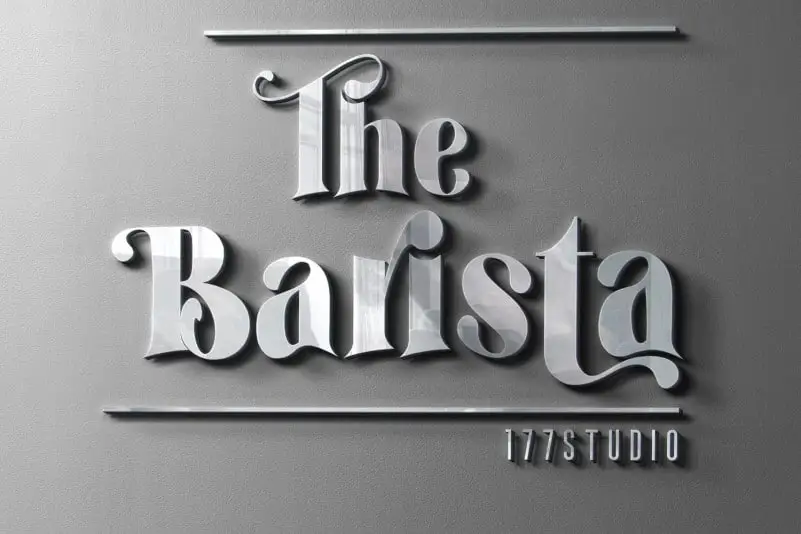
The Barista – Serif Font – Download Grátis
Introduzimos The Barista Serif Font, uma elegante serif que combina detalhes únicos com um toque moderno. Inspirada nas antigas marcas e tipografia vintage, a fonte apresenta belas ligaturas e inúmeras alternativas de caracteres especiais para criar um design sofisticado. Ideal tanto em grandes quanto em pequenos tamanhos, The Barista também oferece uma ampla gama de alternativas estilísticas únicas que permitem personalização completa dos elementos tipográficos. Seja você um designer de logotipos ou criador de materiais promocionais, o The Barista é perfeito para qualquer aplicação. Suportando múltiplas línguas e adequada tanto para nomes de marca quanto para headlines, posters, roupas e muito mais – essa fonte oferece flexibilidade suficiente para atender a uma variedade de necessidades gráficas. Com sua beleza clássica e detalhes atualizados, o The Barista é um verdadeiro power-house no mundo da tipografia.